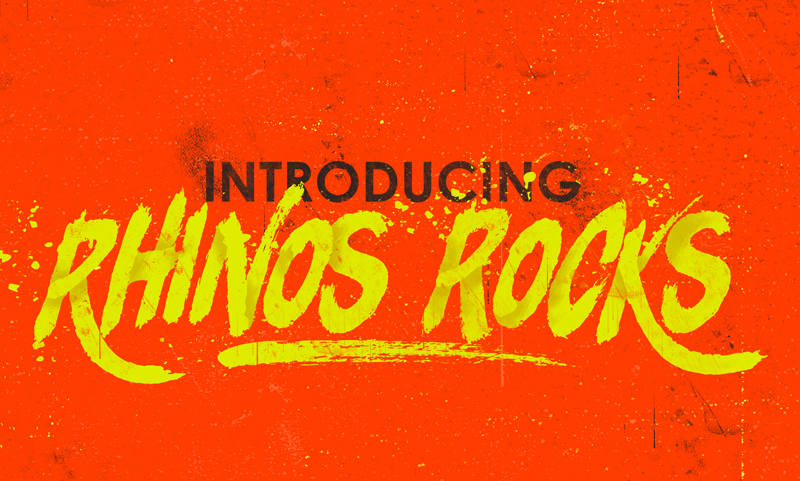
Rhinos Focks Brush Font – Download Grátis
A fonte Rhinos Focks Brush é uma explosão de energia, com traços rápidos e bordas brilhantes. Ela foi criada para transmitir energia e entusiasmo através de mensagens agressivas ou vibrantes. Ideal para uso em logotipos, tags de nome, citações escritas à mão, embalagens de produtos, itens de merchandising, cards de agradecimento e até mesmo t-shirts e outros produtos de vestuário. Sua textura única e sua capacidade de representar sentimentos fortes tornam-a perfeita para um leque de aplicações. Você pode encontrar seu uso em postagens sociais, mensagens importantes ou qualquer outro tipo de material que deseja destacar. A Rhinos Focks Brush é uma fonte versátil e poderosa, capaz de transformar sua mensagem em algo que se destaca no espaço digital e no mundo físico.
Designer: Leonard Posavec – LeoSupply.co